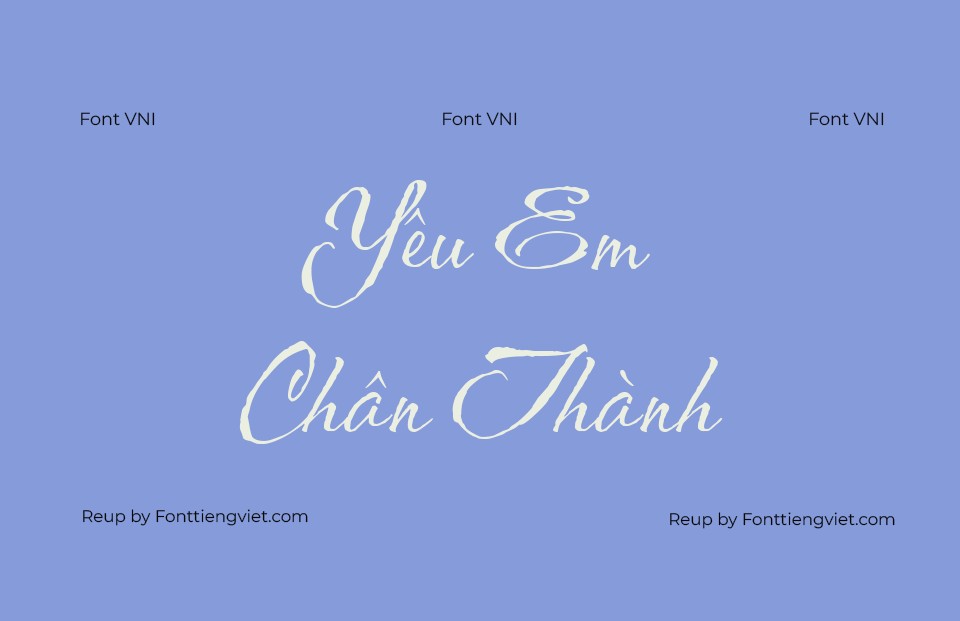
Giới thiệu về Font Việt hoá VNI 30 ShishoniBrush
Trong thế giới thiết kế đồ họa, việc lựa chọn một Font Chữ phù hợp đóng vai trò quan trọng để truyền tải thông điệp một cách trọn vẹn. Font Việt hoá VNI 30 ShishoniBrush là một trong những bộ font mang phong cách cọ vẽ (brush) độc đáo, giúp tạo nên những nét chữ phóng khoáng và nghệ thuật. Với bảng mã VNI truyền thống, bộ font này đã được tinh chỉnh để hiển thị hoàn hảo các dấu tiếng Việt, giúp người dùng không còn lo lắng về lỗi font khi soạn thảo nội dung sáng tạo.
Đặc điểm nổi bật của Font VNI 30 ShishoniBrush
Bộ font này mô phỏng các đường nét viết tay thủ công với những nét thanh nét đậm tự nhiên. Sự mạnh mẽ trong từng nét cọ khiến nó trở thành lựa chọn ưu tiên cho các dự án thiết kế tiêu đề sách, bìa tạp chí hoặc các biểu ngữ sự kiện tại trường học. Không chỉ mang tính thẩm mỹ cao, font chữ còn đảm bảo độ sắc nét khi in ấn trên nhiều chất liệu khác nhau.
Ứng dụng Font Việt hoá VNI 30 ShishoniBrush trong thiết kế
Sáng tạo nội dung giáo dục và nghệ thuật
Đối với học sinh và giáo viên, việc sử dụng Font Việt hoá VNI 30 ShishoniBrush giúp các bài thuyết trình hay tờ báo tường trở nên sinh động hơn. Bạn có thể sử dụng font này để làm nổi bật các câu khẩu hiệu hoặc tên chủ đề chính. Cách cài đặt cũng rất đơn giản, chỉ cần tải tệp tin về máy, giải nén và cài đặt trực tiếp vào hệ thống Windows để sử dụng trên Word, Photoshop hay Canva.